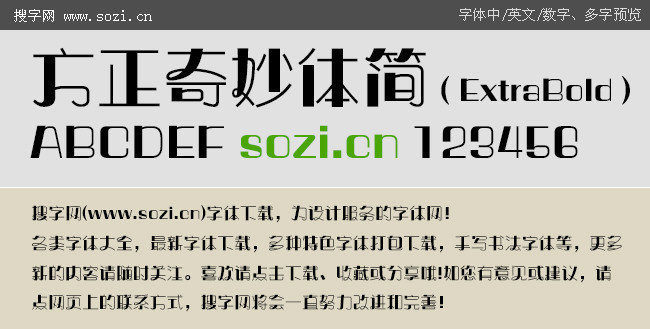
方正奇妙體簡ExtraBold
搜字網(wǎng)提供一款方正奇妙體簡中文字體下載,方正奇妙體風(fēng)格獨(dú)特,時尚高雅,品味出眾,筆劃都以橫細(xì)直粗,增強(qiáng)了美感,充滿個性的字體太誘惑了。共有8種粗細(xì),商業(yè)用途廣泛,男女老少都合適,如手機(jī)字體,動畫,化妝品,女士飾物、時裝、酒店、飲料廣告宣傳和包裝設(shè)計(jì)等!